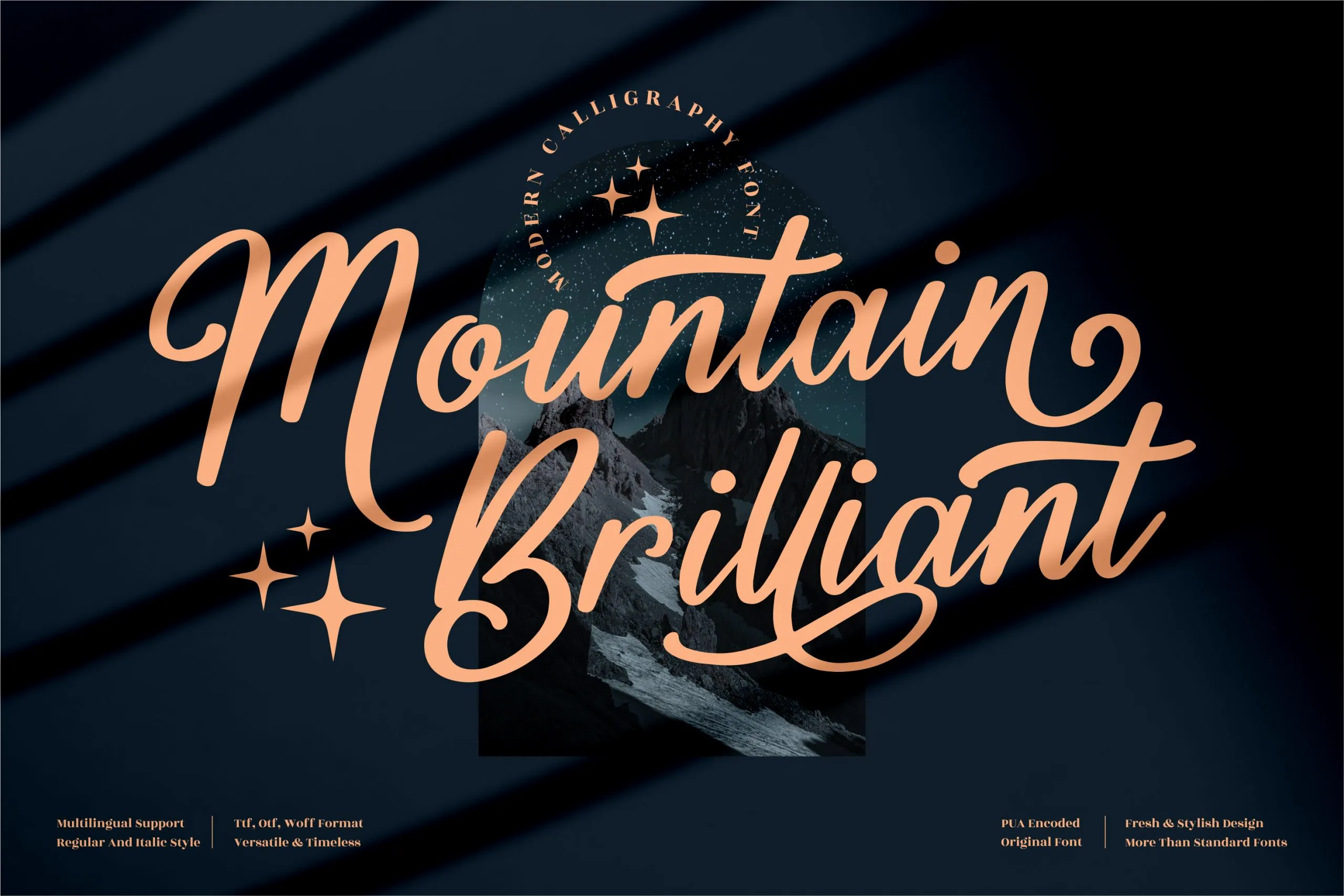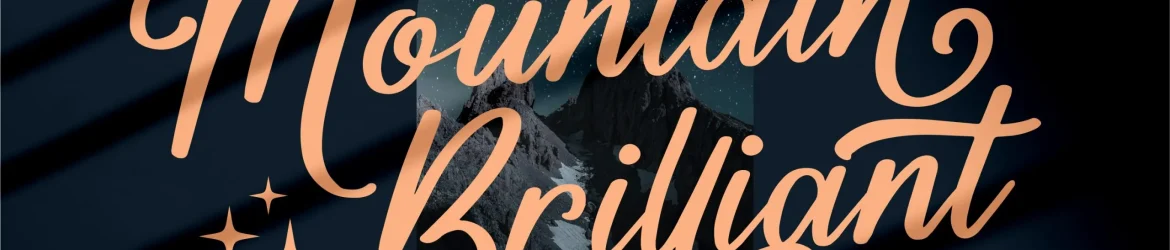
A fonte ‘Mountain Brilliant Font’ é uma elegante escolha para qualquer projeto que exige um toque sofisticado. Especialmente adequada para trabalhos de estilo script, ela se destaca como uma opção premium, ideal para criar uma sensação de luxo e exclusividade em diversas áreas da design gráfico. Seja para desenvolver o logo de sua marca, criar embalagens de produtos ou até mesmo personalizar um convite especial, ‘Mountain Brilliant Font’ oferece a capacidade de dar vida ao seu trabalho com um toque autêntico e sofisticado que se destaca no meio da massa. Com design cuidadosamente criado para oferecer uma variedade de opções de estilo e interação, esta fonte é perfeita para qualquer projeto que busque transparência e elegância em cada letra impressa.